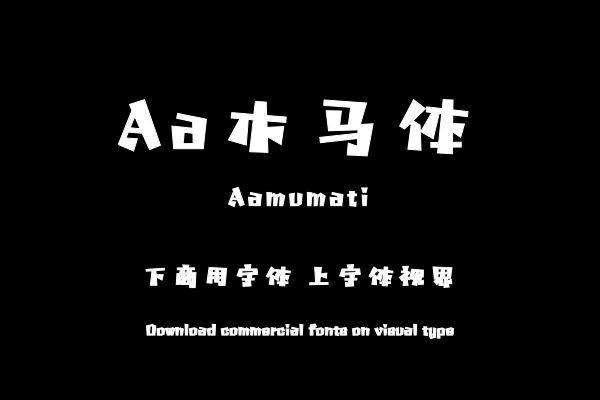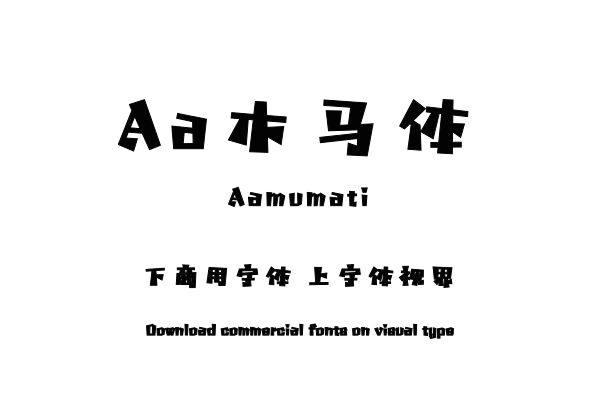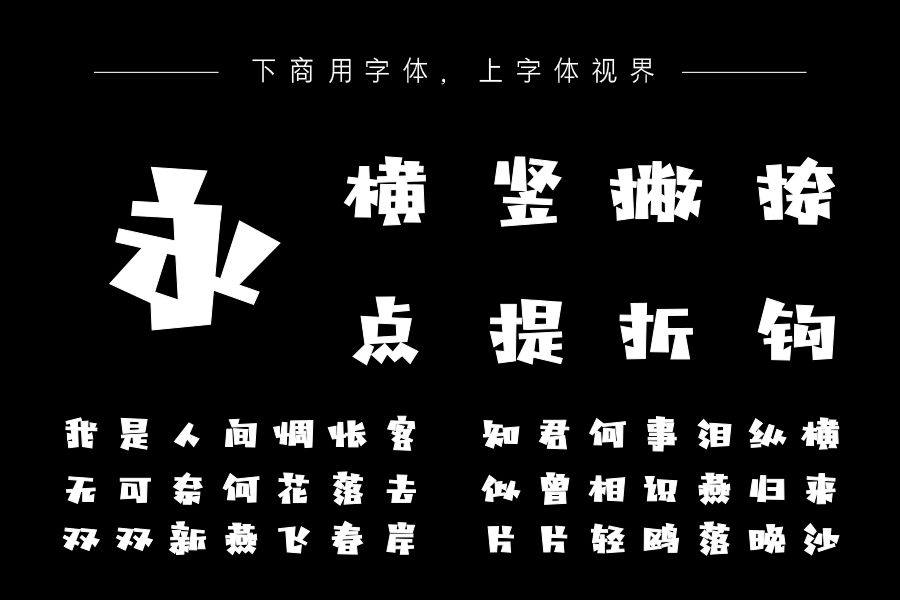
以粗细两种方头笔画制作一款卡通感标题字体。榫卯般的方头笔画好像木匠任意而为的奇异家具,宽大的中宫和自由的结构都增强了有趣的卡通感。购买须知:“下载服务费”与“字体VIP”所获得字体 仅用于个人非商用, 商用请联系付费授权。本字体为电脑用字,手机没有root权限不支持直接手机换字(手机如何root,请自行百度搜索教程)。购买前请先 了解清楚后再付款 ,字体为虚拟产品无法回收 一旦购买不支持退款。